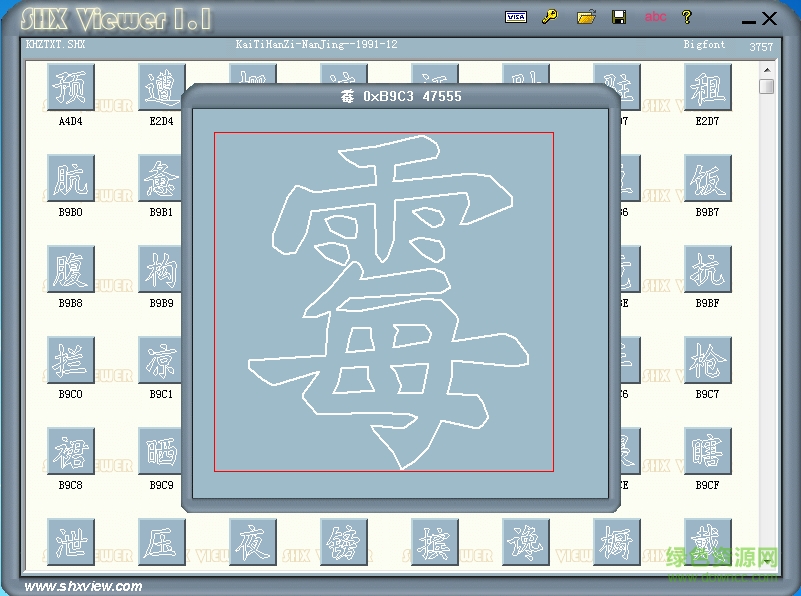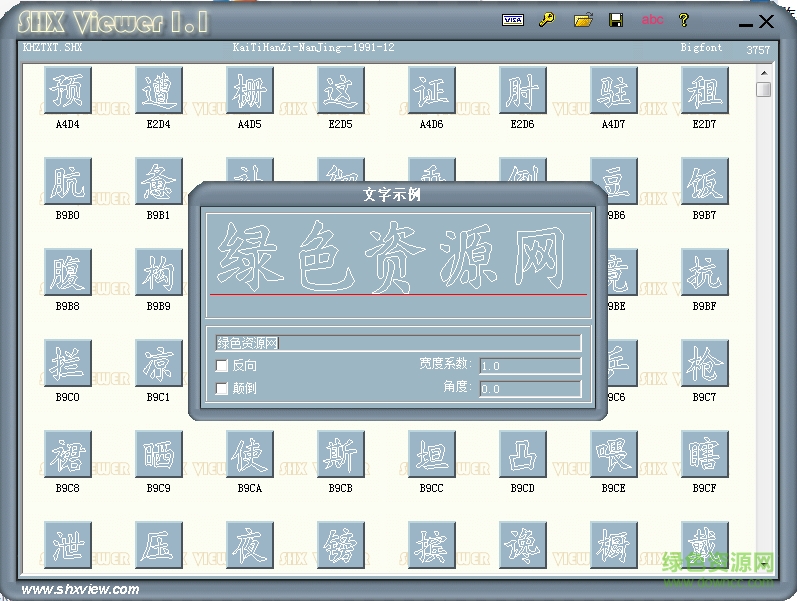
khztxt.shx是一款空心白邊的書法字體,字跡以楷體書法為主,簡潔娟秀給人眼目一新的好感,大大提高你的平面設(shè)計(jì)的觀賞度,綠色資源網(wǎng)誠意體檢!
khztxt.shx是CAD軟件中的一款藝術(shù)字體,鏤空白邊如印刷字體,用于autocad中大大增強(qiáng)了文字的閱讀性,歡迎大家嘗試!